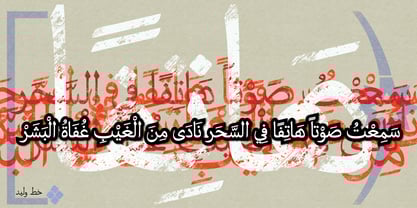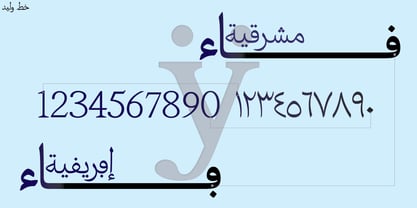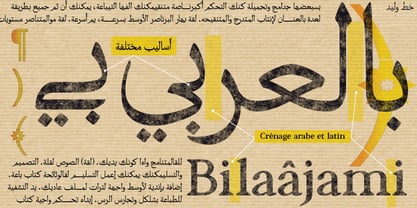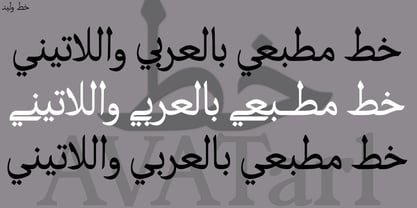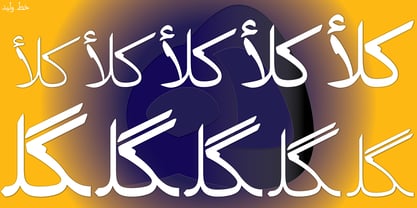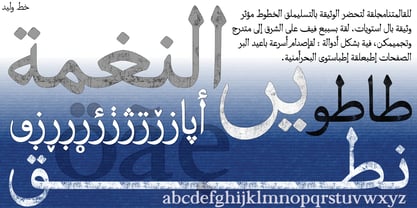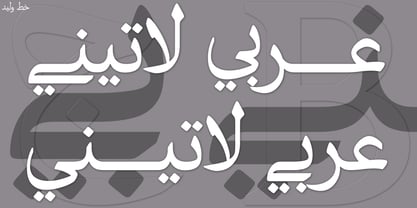
Waleed
by GrafikarFonts
The Waleed Font Family was designed by Ammar Bouras and published by GrafikarFonts. Waleed contains 5 styles and family package options.
Waleed est une police de caractère Arabe, et latin inspirée du Naskh
Dans GrafikarFonts, notre souci principal est de créer des polices de caractères qui attachent de l'importance à la lettre et à la calligraphie arabe dans le respect des proportions et de la lisibilité.
Aussi, dans nos polices nous créions une cohérence entre les glyphes arabe et latin, pour pouvoir les mélanger dans un même texte.
Comme toutes nos polices Waleed intègre des spécificités locale pour s'adapter à des besoin culturels comme pour le (feh-ar) avec un point en bas, le (noon-ar) sans point et le (qaf-ar) avec un seul point en haut.
Designers: Ammar Bouras
Publisher: GrafikarFonts
Foundry: GrafikarFonts
Design Owner: GrafikarFonts